Contraste inversé
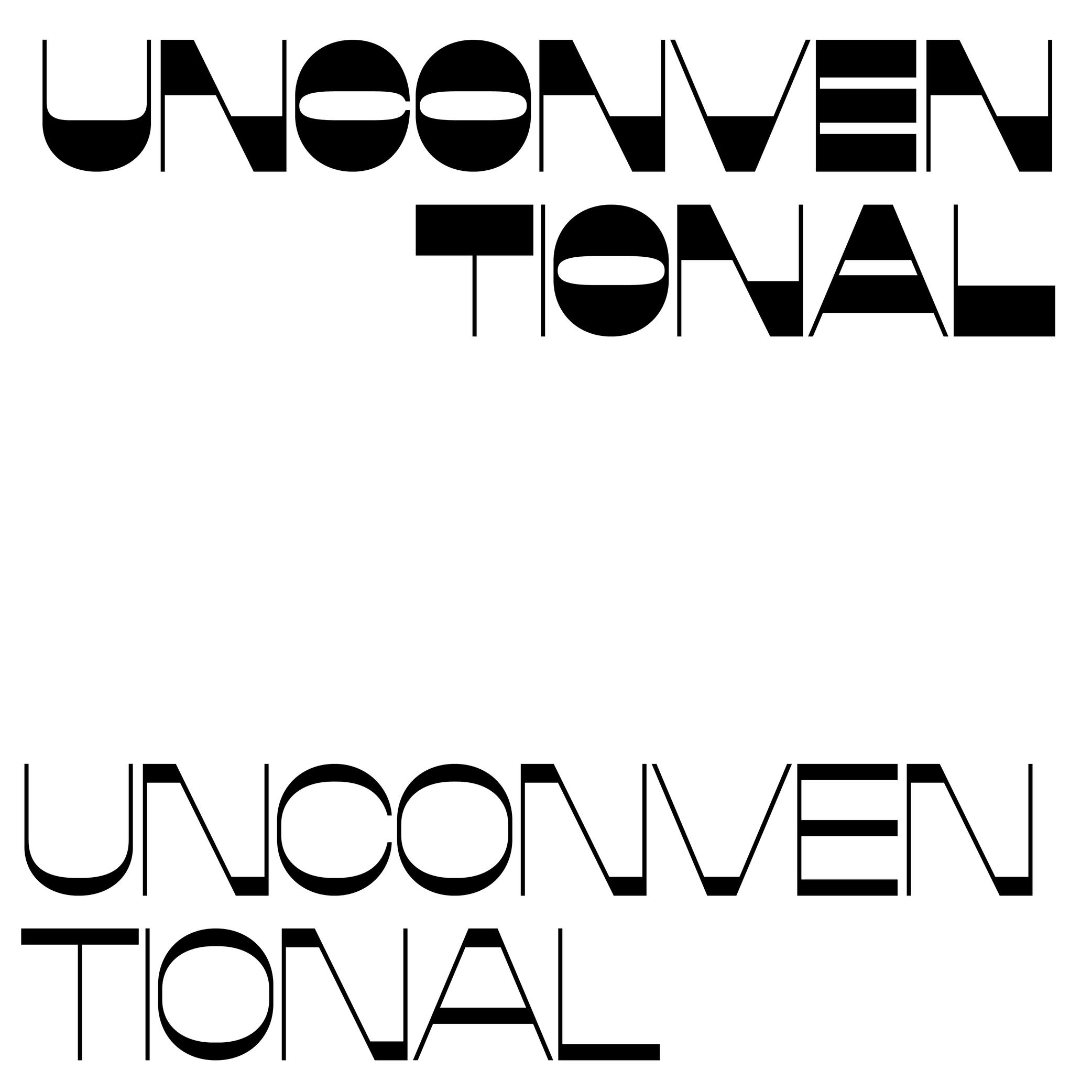
Le contraste est le rapport entre les pleins (parties épaisses) et les déliés (parties fines) des glyphes.
Ces variations d’épaisseurs du trait viennent de l’écriture manuscrite, résultat de l’outil qui interagit avec son support en combinaison avec les mouvements de l’écrivain.
Aujourd’hui, en dessin de caractères latins, on parle de contraste vertical ou naturel lorsque les parties verticales sont plus épaisses que les horizontales. Le contraire est un contraste inversé.
Mais ces concepts ne sont applicables qu’à des écritures ayant évolué en utilisant des outils et supports qui créent naturellement un tel effet, ce qui n’est pas le cas pour tous. Par exemple, le contraste de l’alphabet hébreu est « naturellement » distribué dans le sens inverse.